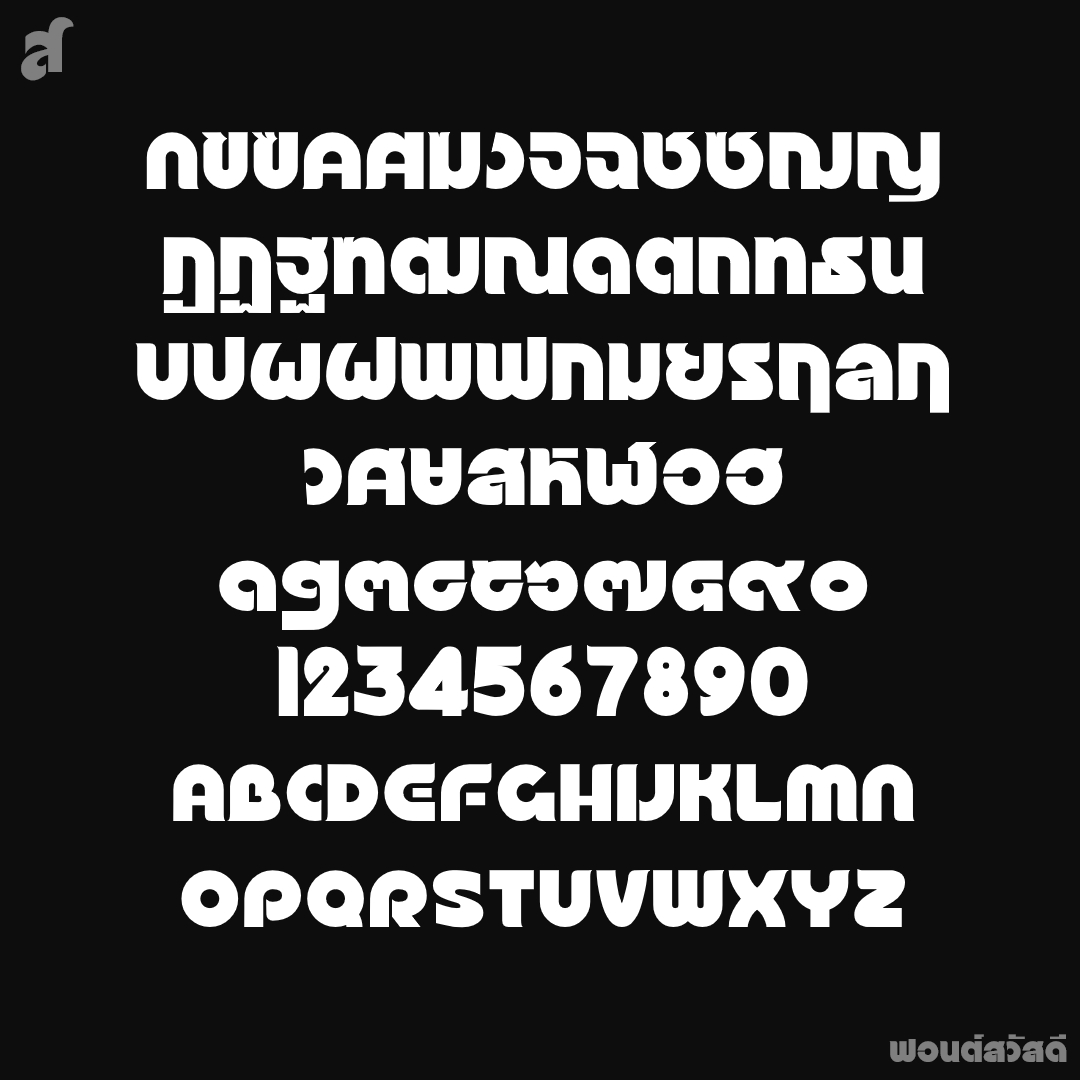
ฟอนต์ สวัสดี
ที่มาจากโฆษณาภาพยนต์ ล่าพญายม ในหนังสือพิมพ์ ต้นปี ๒๕๑๘ อักษรไม่มีหัวตัวกลมบ็อก เมื่อกว่า 50 ปีที่แล้ว ..แอบสบัดปลายน้อยๆเพิ่มเข้าไปหน่อยนึงเน่อ  ปล.แล้วก็ไม่ได้ทำ kerning ให้นะจ๊ะ..อย่าลืมเอาไปขยับเอง
ชื่อฟอนต์ : สวัสดี
ที่มาจากโฆษณาภาพยนต์ ล่าพญายม ในหนังสือพิมพ์ ต้นปี ๒๕๑๘ อักษรไม่มีหัวตัวกลมบ็อก เมื่อกว่า 50 ปีที่แล้ว ..แอบสบัดปลายน้อยๆเพิ่มเข้าไปหน่อยนึงเน่อ  ปล.แล้วก็ไม่ได้ทำ kerning ให้นะจ๊ะ..อย่าลืมเอาไปขยับเอง